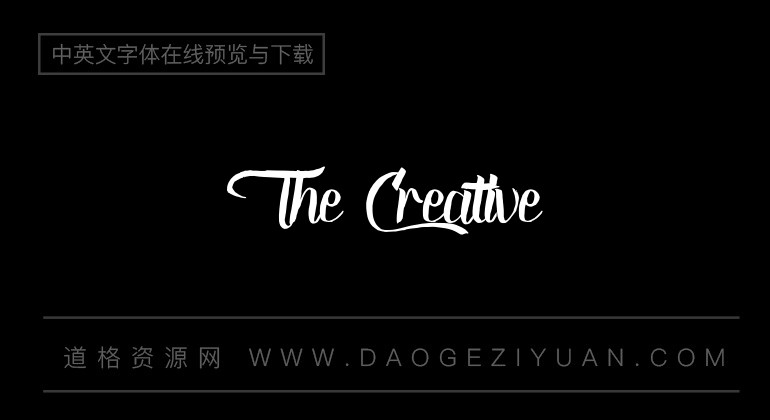
The Creative 字体是一款极具创意的英文字体,它采用了抽象的设计风格,拥有无限的可能性,可以为您的设计添加更多的创意元素。The Creative 字体的字形特点是视觉上的复杂性,具有细节性,并且具有独特的外观,可以为您的设计带来更多的创意灵感。内容介绍
The Creative是一款非常不错的手写艺术字体,具有很好的视觉感,适合于文化类的宣传设计、商业类品牌的广告和产品包装设计以及个性化文字排版等较多场景。